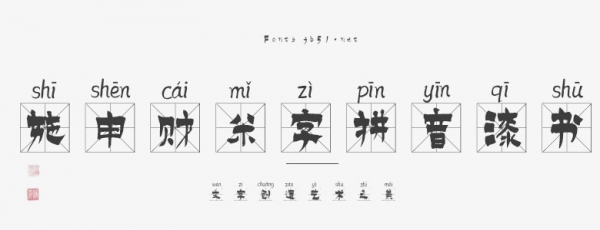
施申財(cái)米字拼音漆書是一款書寫很新穎的字體,自帶拼音標(biāo)注效果,具有強(qiáng)烈的視覺(jué)沖擊力。適用于海報(bào)、電商海報(bào)設(shè)計(jì)、店鋪設(shè)計(jì)、標(biāo)志設(shè)計(jì)、字體設(shè)計(jì)等領(lǐng)域。
施申財(cái)米字拼音漆書